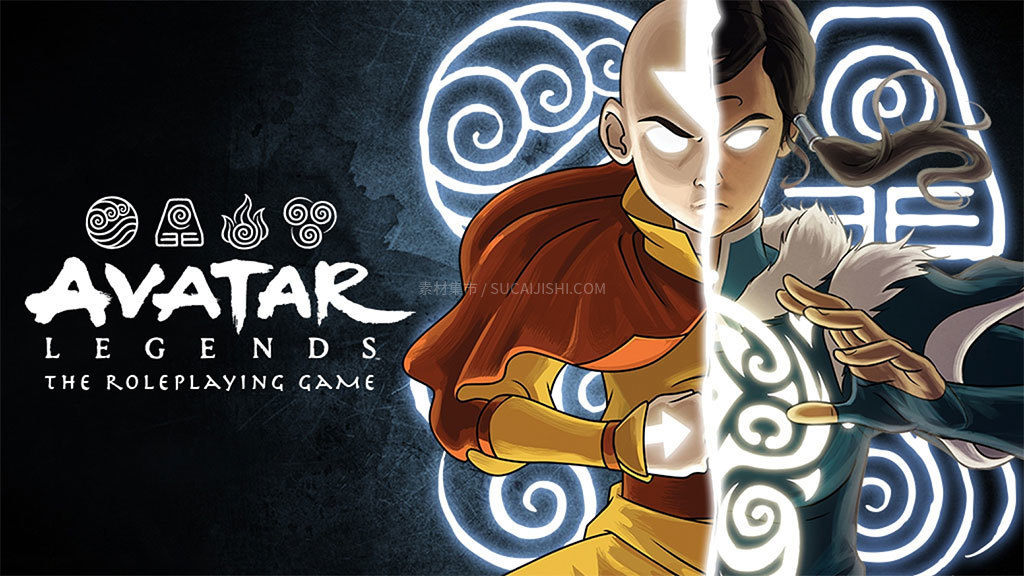
童年回忆杀!《降世神通:最后的气宗》同款字体
经典美国动画《降世神通:最后的气宗》绝对是很多人的童年神作!看最后的气宗大师安昂掌握四种元素、对抗烈火国的故事真的超级燃。今天给大家挖到了这部动画Logo的同款平替字体!
童年回忆杀!《降世神通:最后的气宗》同款字体主视觉“Avatar”虽然是官方定制的,但 FontGet 出品的“Avatar Airbender”字体完美还原了那种带有东方奇幻和元素武术色彩的气韵,而且可以免费使用!
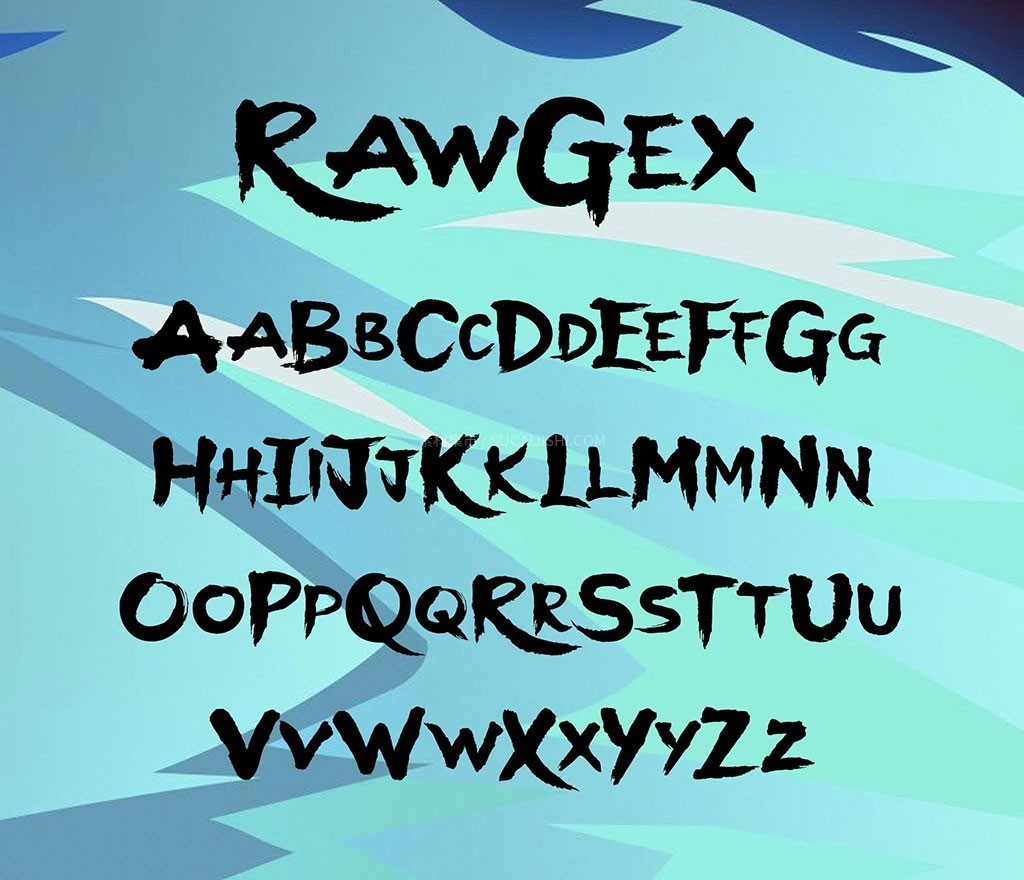
至于底下“The Last Airbender”的部分,直接用“Herculanum Roman”这款字体就能轻松拿捏,相似度极高。
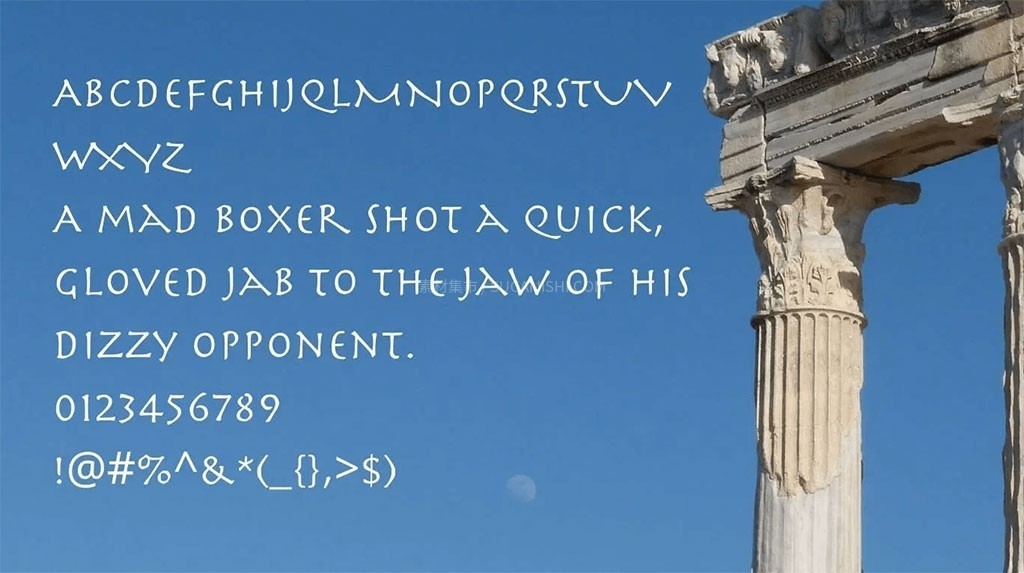
这款字拿去当快餐店或者奶茶店的菜单排版也很不错啊,看着就让人很有食欲。